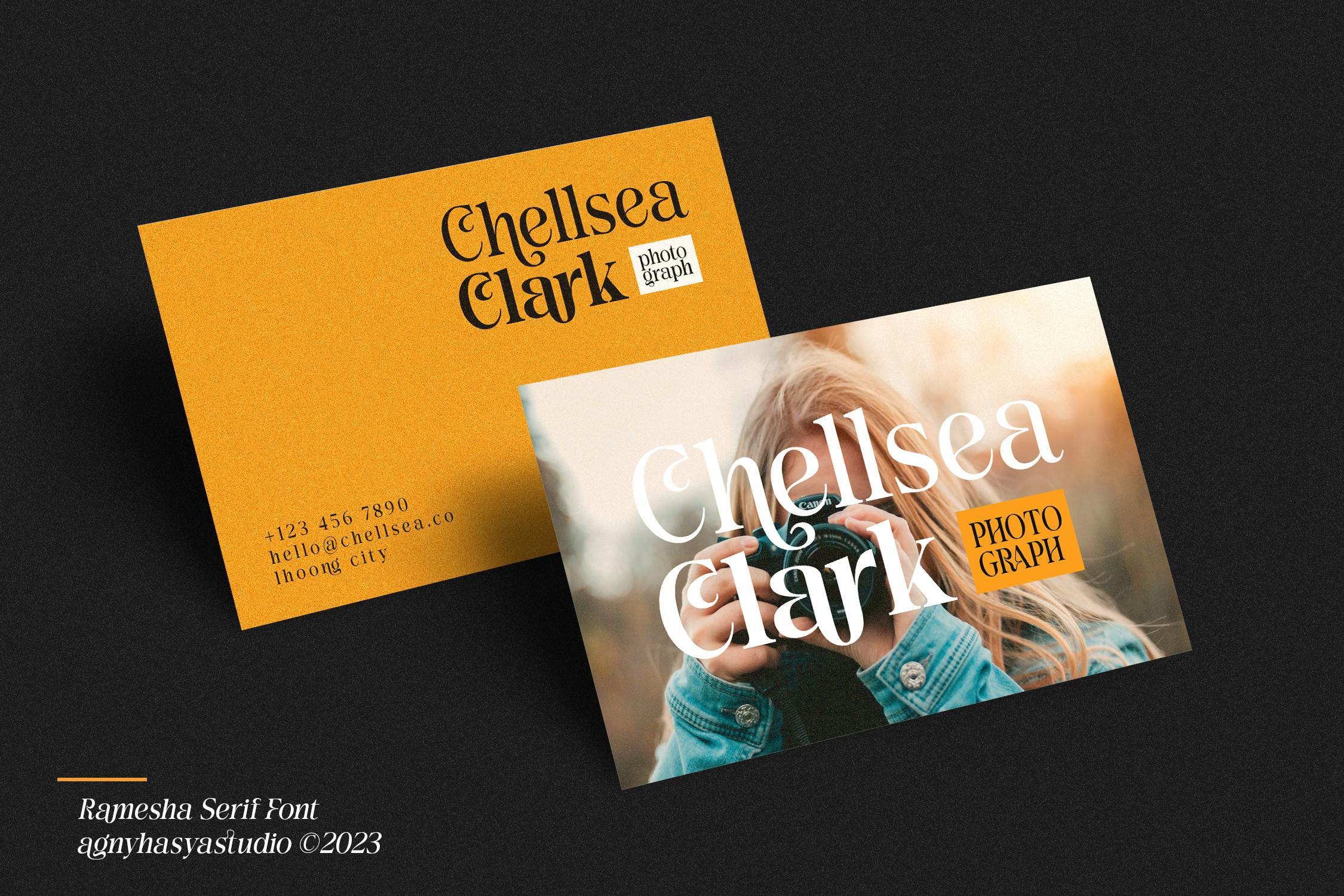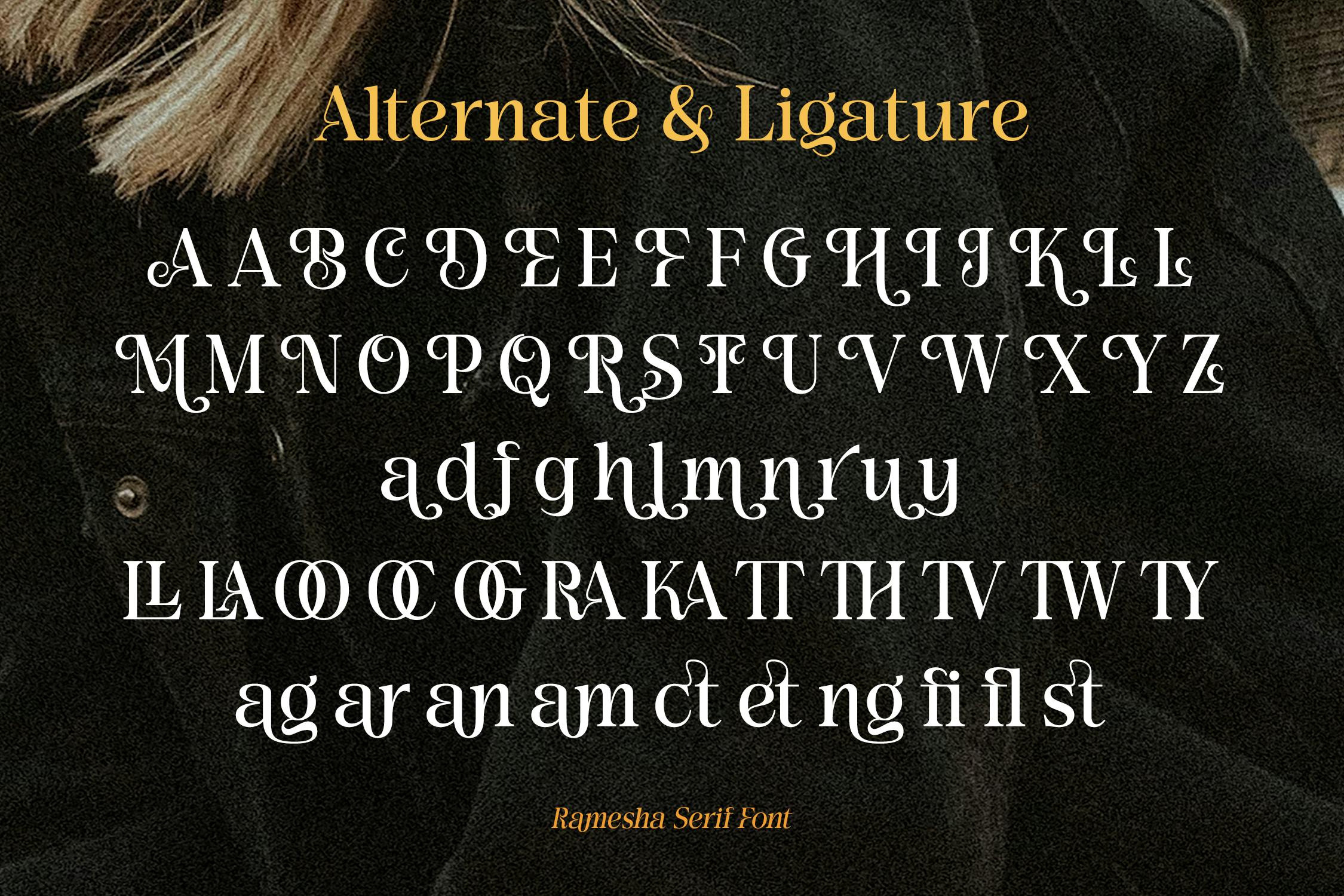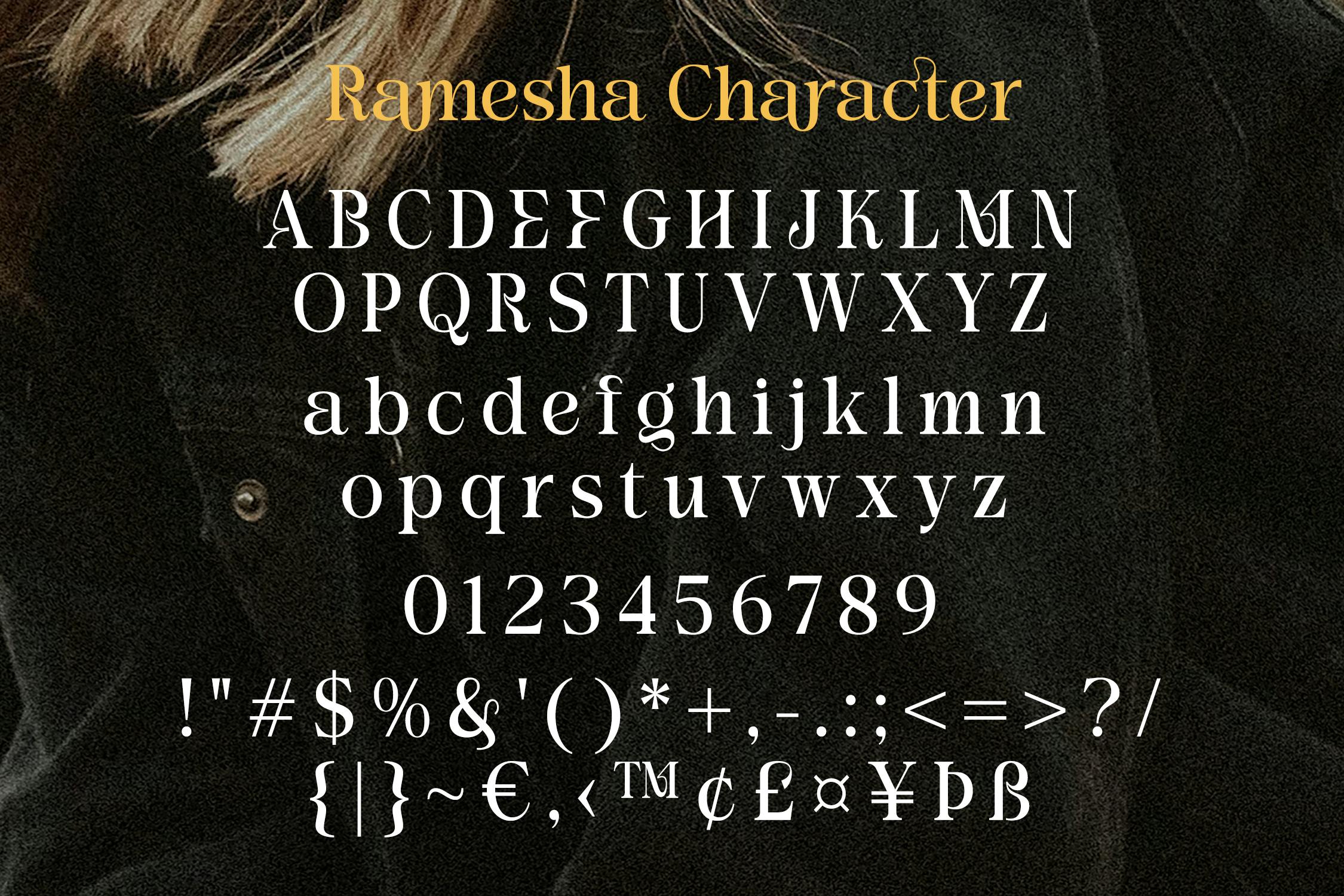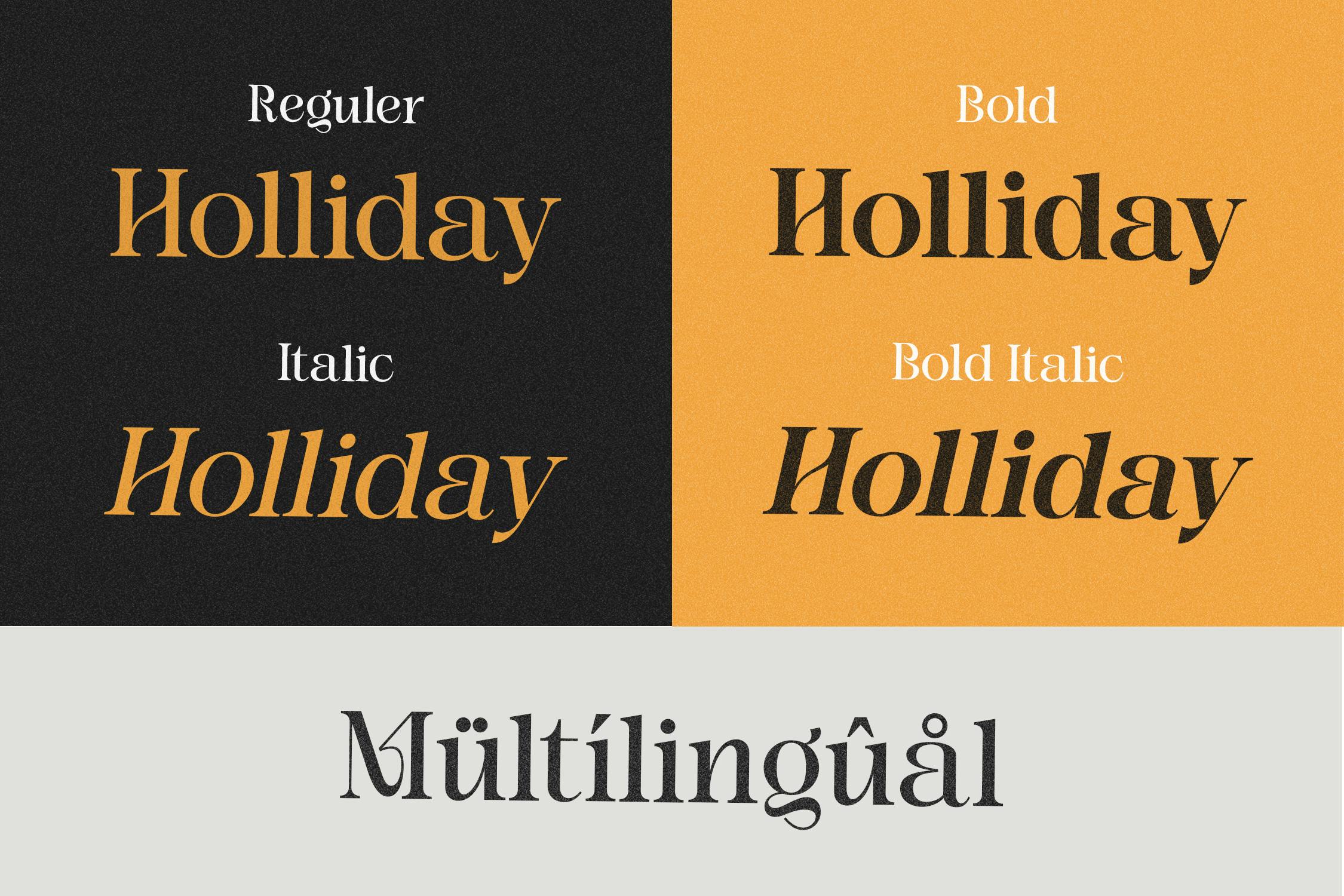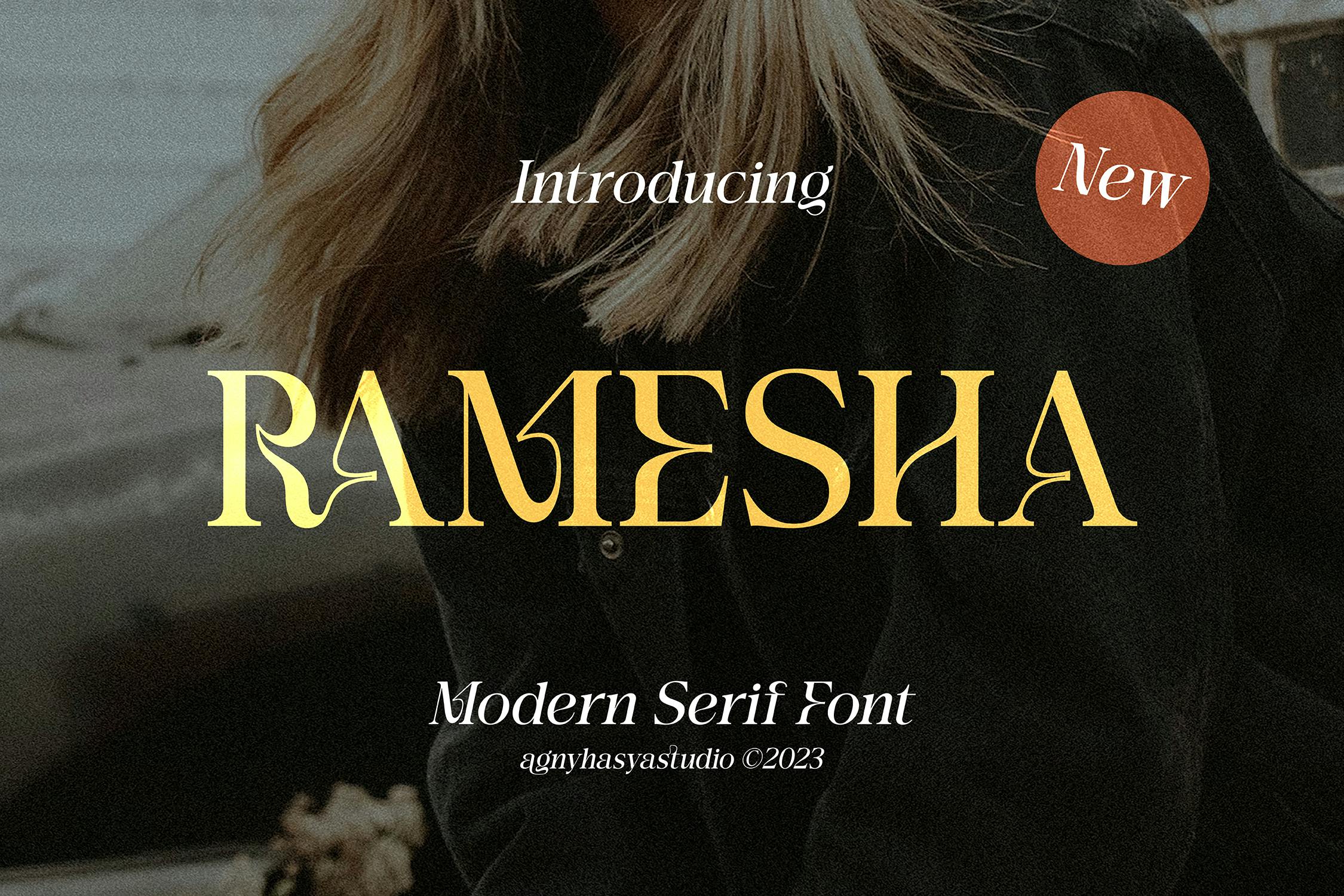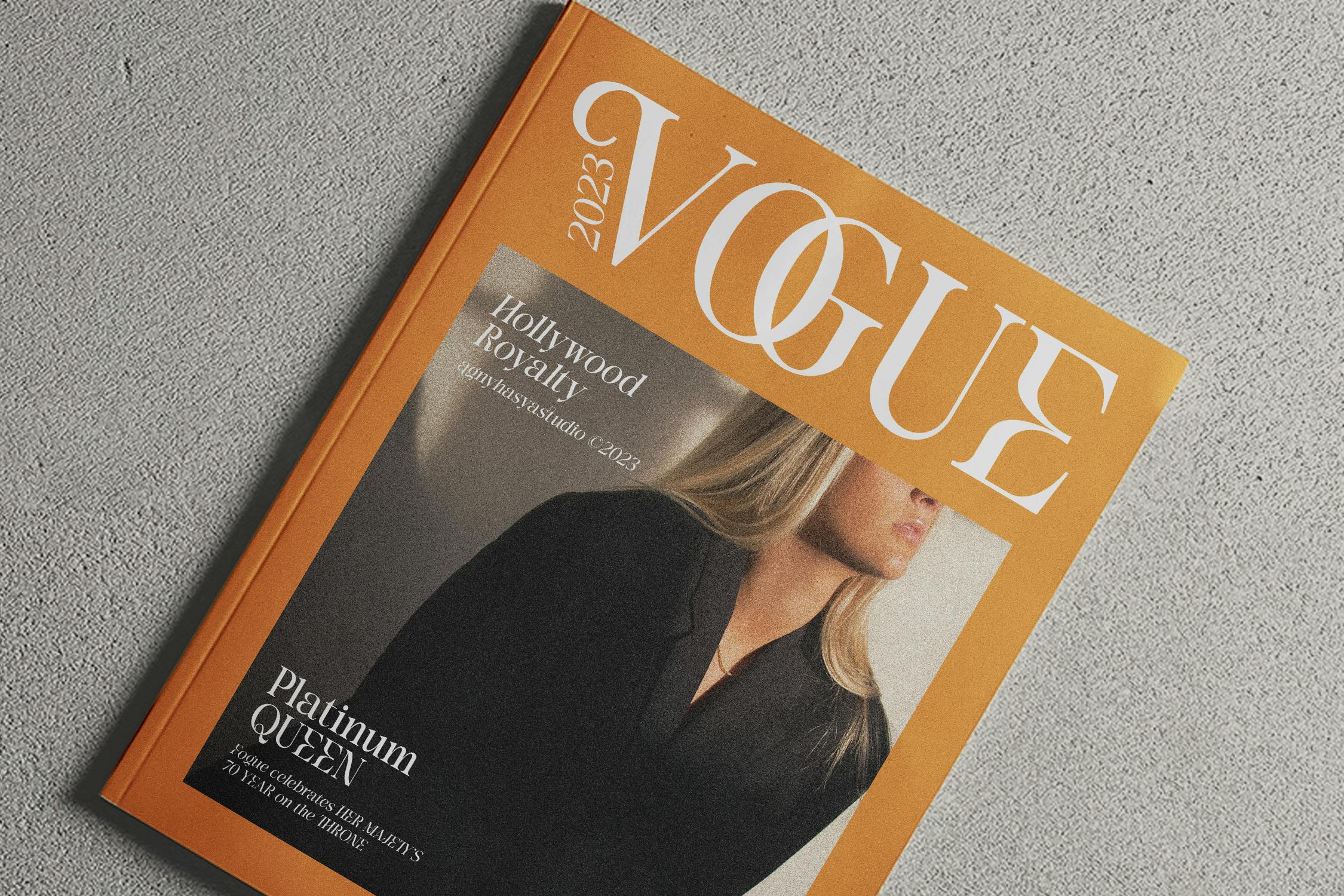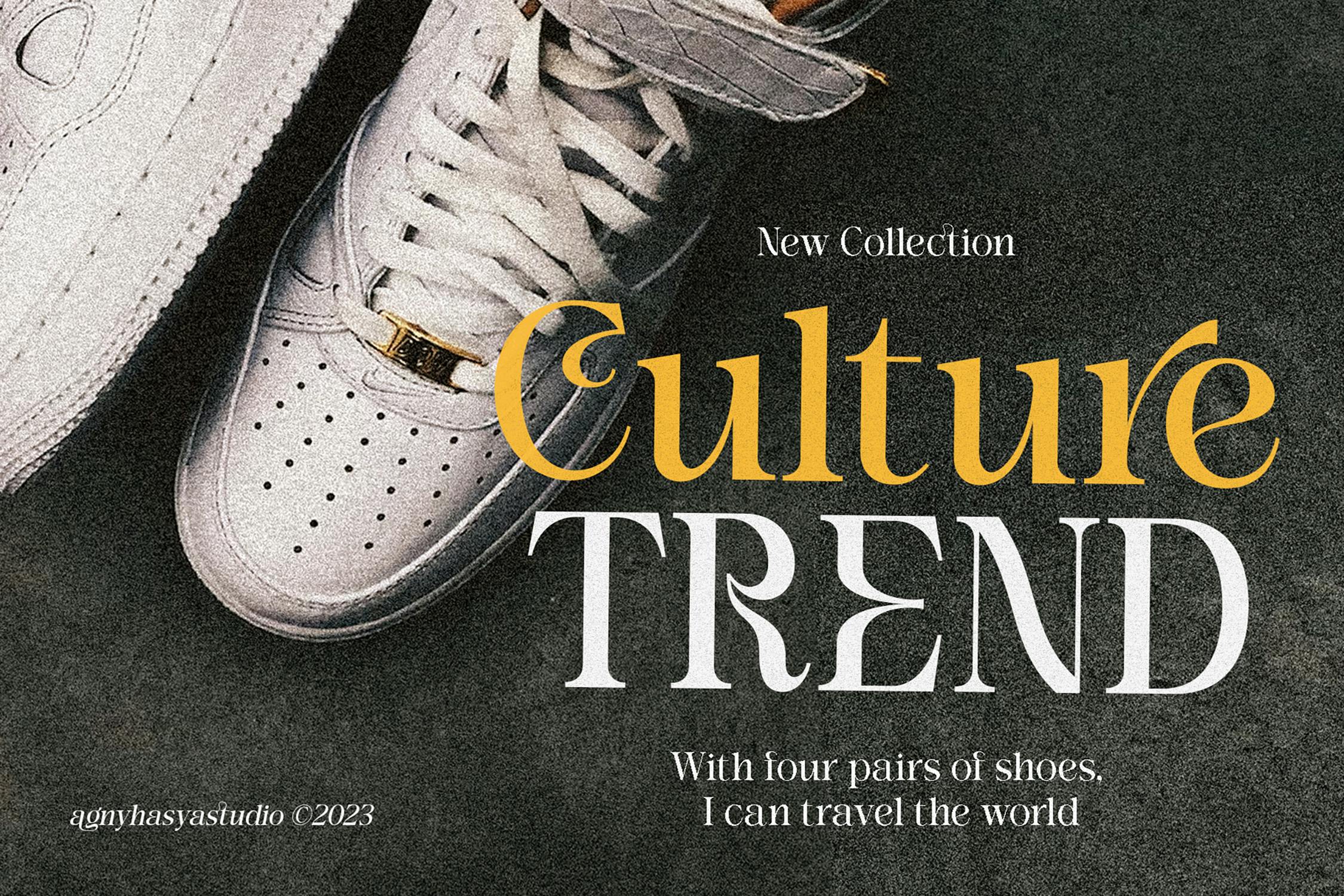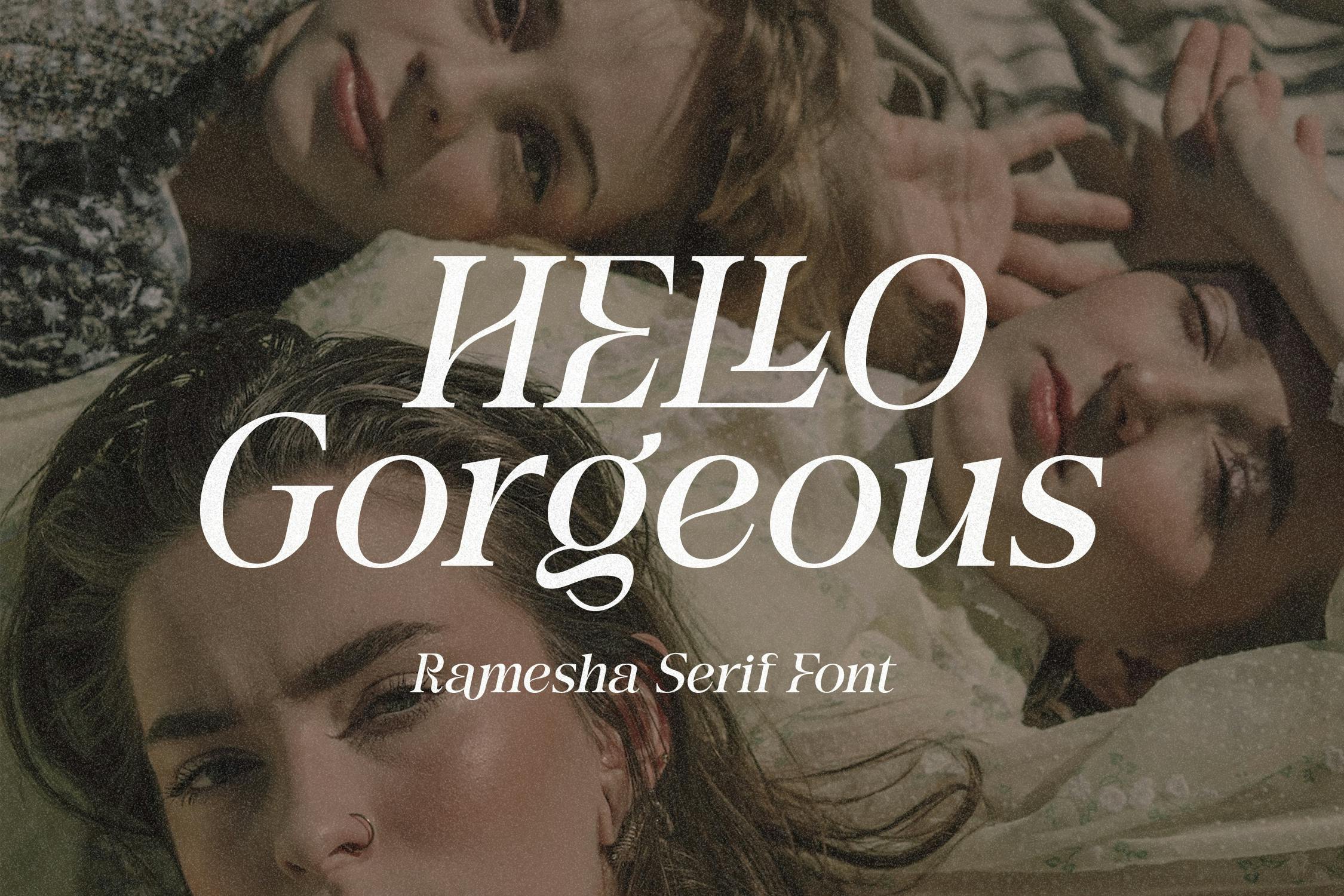
معرفی Ramesha - فونت مدرن Serif
Ramesha یک تایپفیس مدرن و شیک با طراحی Serif است که با تنوع در گلیفها مانند جایگزینها و لیگاتورها ایجاد شده است. آن را ترکیب کنید و طراحی تایپوگرافی فوقالعاده خود را بسازید!
این فونت برای پروژههای طراحی شما مانند لوگوها، برندینگ، تبلیغات، طراحی محصولات، لوازمالتحریر، طراحی مجله، عناوین کتاب، عکاسی، نقلقولهای هنری، طراحی عروسی، طراحی مد، رویدادهای خاص، برچسبها، بستهبندی محصولات و بیشتر بسیار مناسب است.